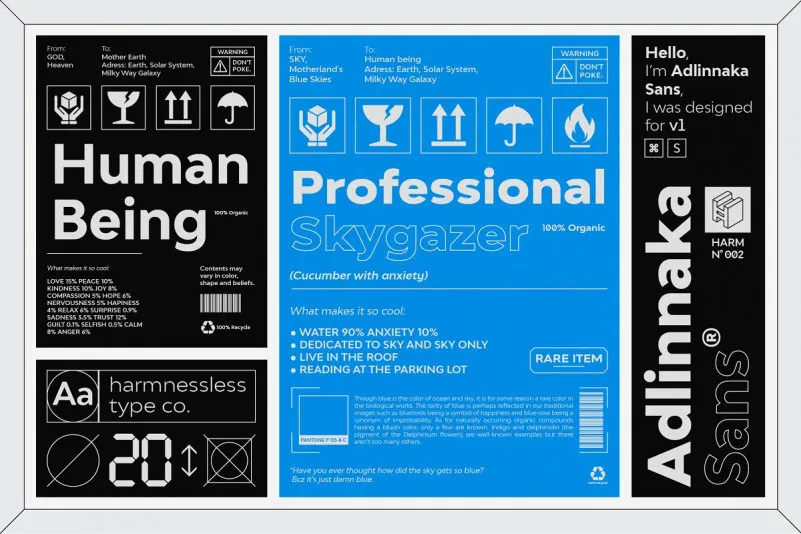
A Adlinnaka Font Family é uma moderna tipografia sans serif que oferece 9 pesos diferentes incluindo itálico (totalizando 52 fontes). Ela apresenta uma aparência robusta que fará seu melhor para criar títulos e headlines atraentes. Este design foi criado e compartilhado pelo harmnessless, designer de renome. A Adlinnaka Sans é um sans geométrico humanoista com detalhes aguçados e arranjo distintivo, o que expande ainda mais as limitações do x-height fornecendo uma flexibilidade sem precedentes. Com alta legibilidade, esta fonte oferece estilos perfeitos para ambientes de exibição e cópia corpo. Adlinnaka é um recurso visual poderoso que se destaca em qualquer design, especialmente quando você precisa chamar a atenção com títulos ou headlines impactantes.